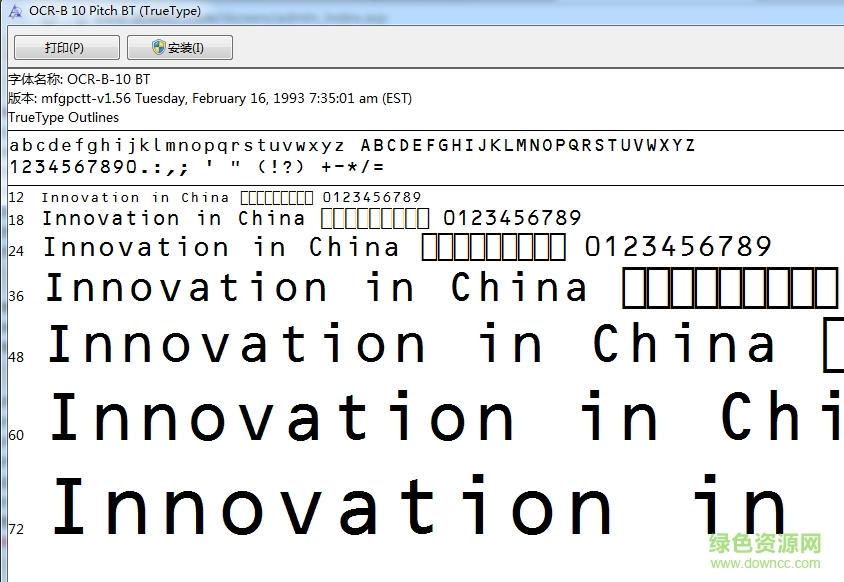
OCR-B 10 bt(商品条形码和身份证号字体)
OCR-B 10 BT字体是商品条形码和身份证号的数字字体及PS的最佳伴侣,这款字体的效果和身份证号上的字体是一样的,用户能够通过使用这款字体打出非常标准的数字来,在平时的商品条形码中也是经常用到。需要的朋友就赶快来绿色资源网下载使用吧!
OCR-B 10 BT字体介绍